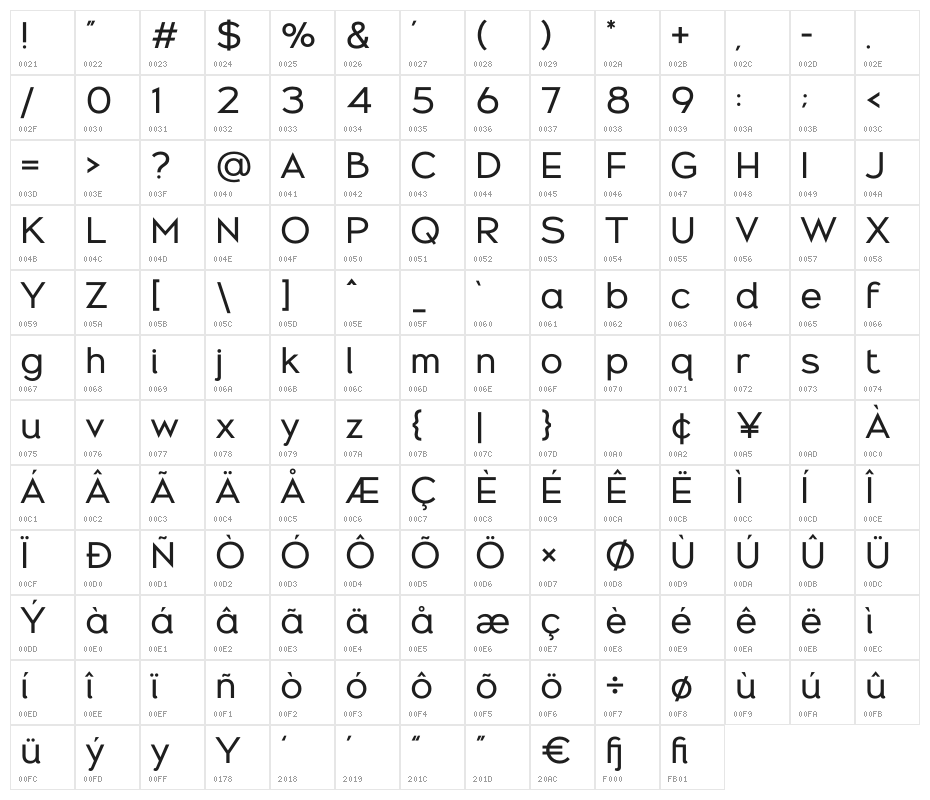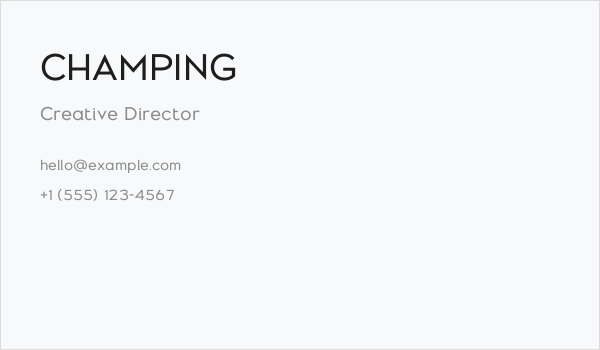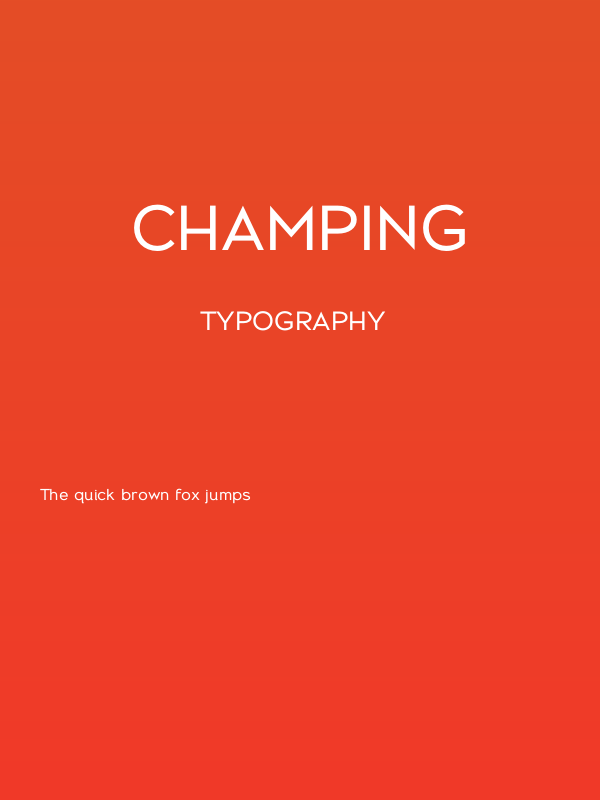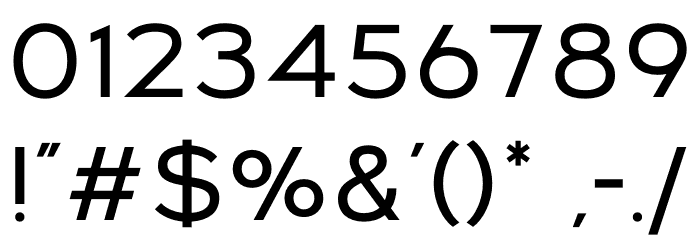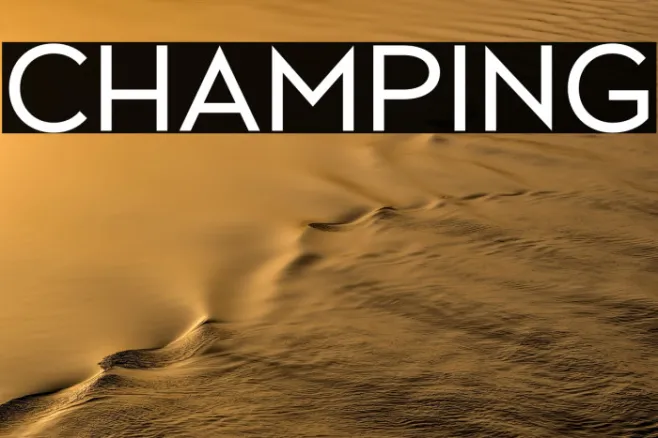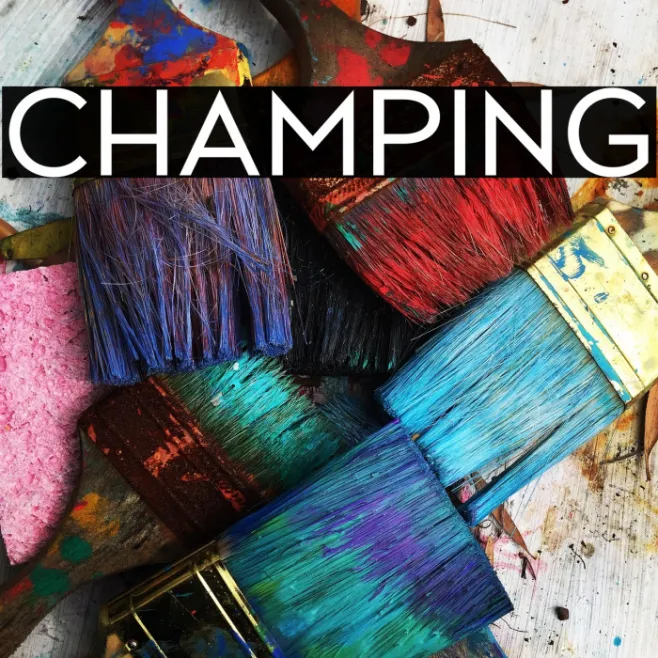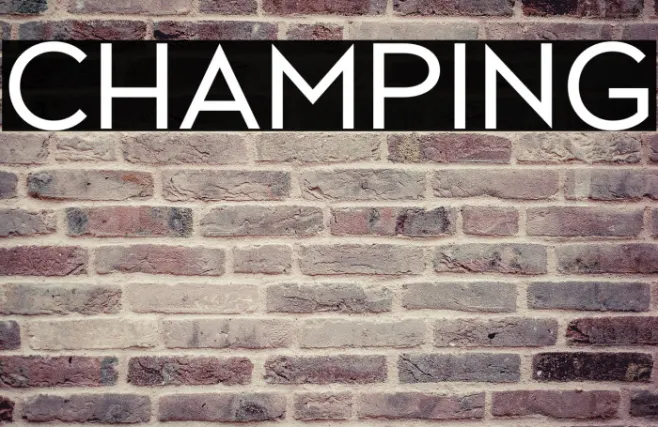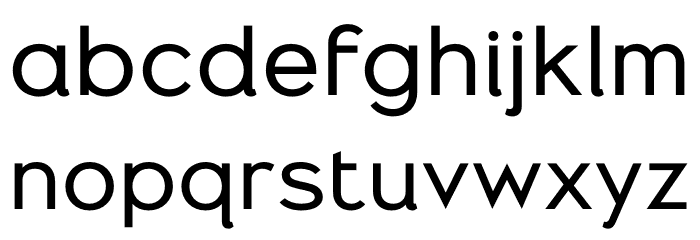
CHAMPING Font
✎ Sans Serif
| Kategorien | Sans Serif |
| Anwendungsfall | Headlines, Body text, Logos |
| Vorgeschlagene Projekte | Ideal for branding, web design, advertising, and editorial projects where clarity and modernity are essential. |